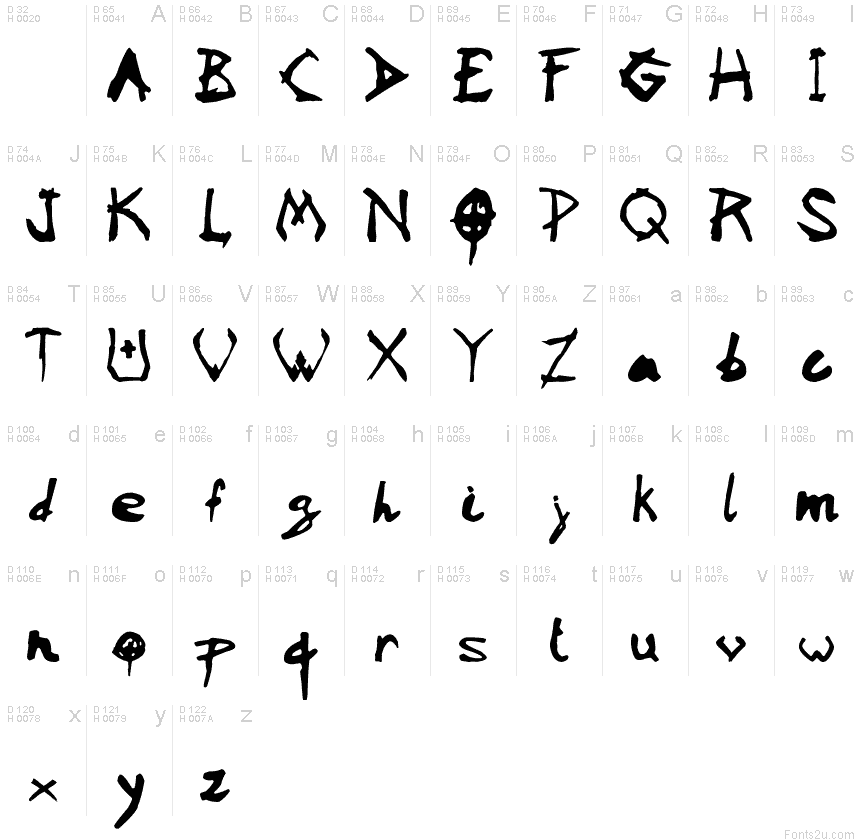
Vaudoo 2 RF to darmowy, przerażający krój wyświetleniowy o surowym, voodoo-stylu. Litery wyglądają jak namalowane w pośpiechu, są niestabilne, z nabrzmiałymi krzywiznami, zwężającymi się pociągnięciami i kapiącymi zakończeniami, dzięki czemu cały krój sprawia wrażenie rytualnego, a nie tylko strasznego.
Idealnie pasuje do plakatów horrorów, ulotek na mroczne imprezy, tytułów gier, opakowań na Halloween i złowieszczych nagłówków, gdzie kilka słów musi wyglądać na odręcznie stworzone i nieco przeklęte. Jako darmowy font, Vaudoo 2 RF najlepiej sprawdza się w krótkich formach, logo, monogramach lub inicjałach, ponieważ jego nieregularne sylwetki i detale przypominające ściekający atrament budują nastrój, zanim jeszcze zdążysz przeczytać słowo.